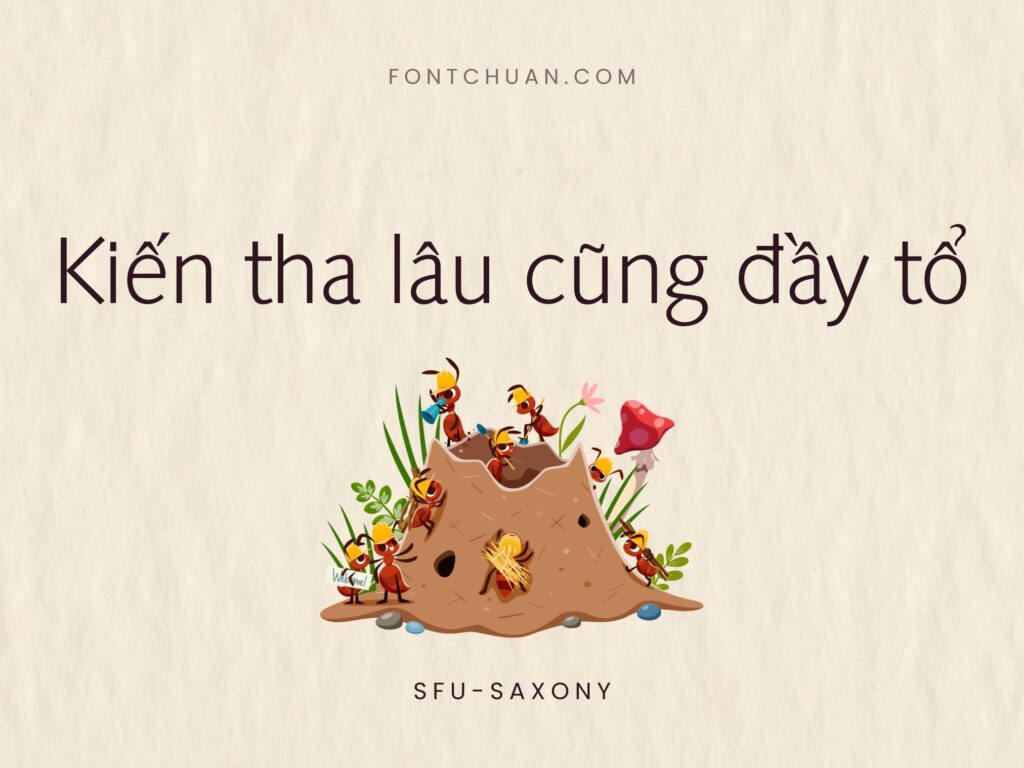
Font SFU Saxony Việt Hóa
Font SFU Saxony Light là một kiểu chữ sans-serif thanh mảnh, được thiết kế với các đường nét tinh tế và hiện đại, tạo cảm giác nhẹ nhàng và chuyên nghiệp. Font này thích hợp cho nhiều mục đích sử dụng khác nhau, từ văn bản nội dung đến tiêu đề và thiết kế đồ họa.
SFU Saxony Light lý tưởng cho các dự án thiết kế logo, tiêu đề, bao bì sản phẩm và các ấn phẩm quảng cáo. Các ngành nghề như quảng cáo, giáo dục và công nghệ có thể tận dụng font này để tạo điểm nhấn trong thiết kế. Ngoài ra, font cũng thích hợp cho các sự kiện như Tết, Giáng sinh, Valentine và các lễ hội khác.